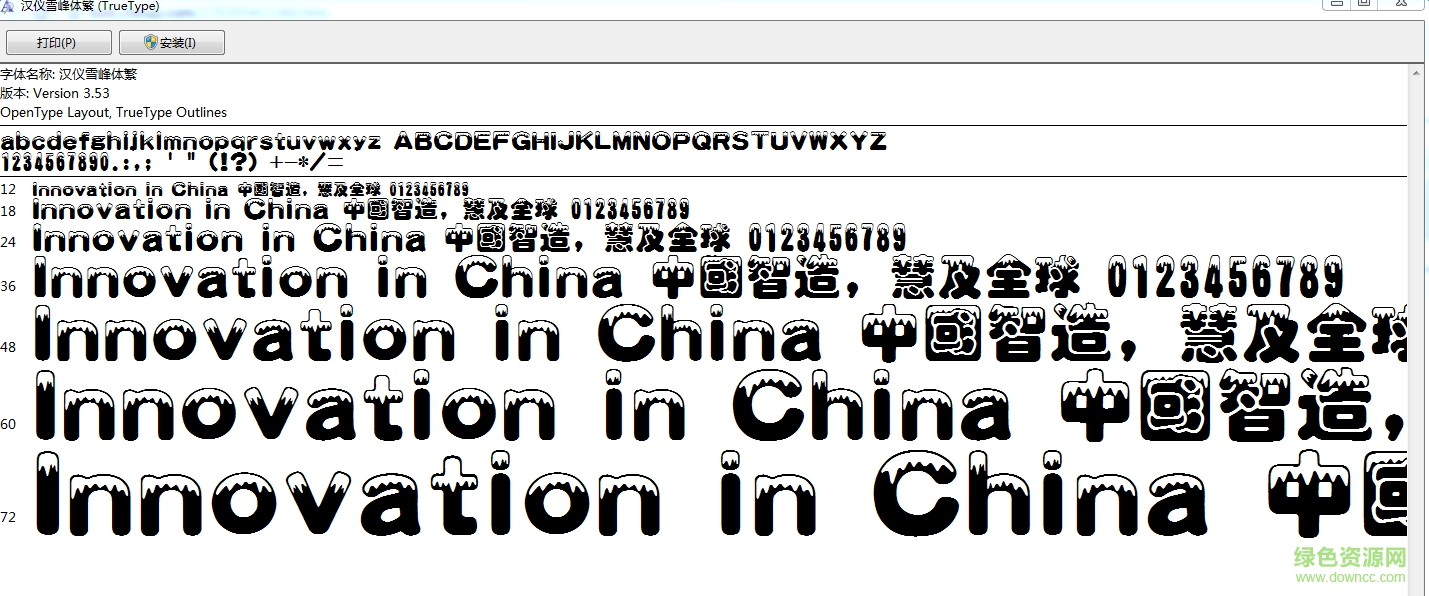
hyo2gj字體就是漢儀雪峰體,這款字體外形就像雪峰一樣,字體風(fēng)格非常獨(dú)特,很受設(shè)計(jì)師們的喜愛!需要的朋友歡迎來綠色資源網(wǎng)下載安裝。
hyo2gj是像雪峰一樣的個(gè)性字體,字體筆畫較粗,上白下黑,用在廣告設(shè)計(jì)、平面設(shè)計(jì)或相關(guān)的包裝設(shè)計(jì)方面效果十分好!
該字體每個(gè)字頂上都宛如白雪飄零,高低錯(cuò)落,似山頂上的雪峰,是不是很有個(gè)性呢?